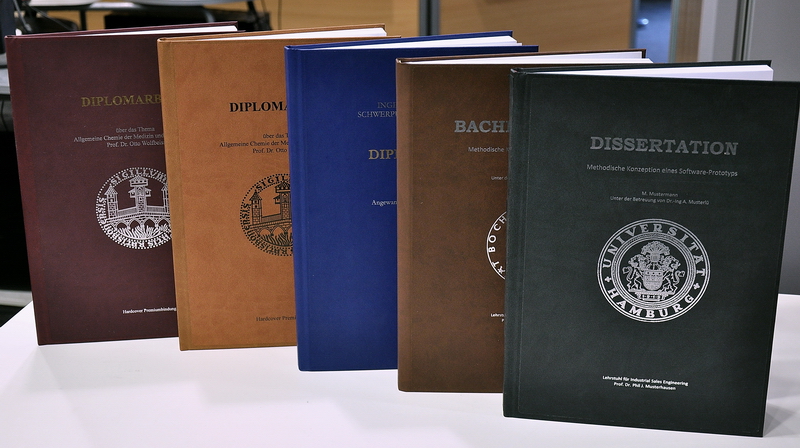
Suche Schriftart für Prägung Bachelorarbeit (Bild anbei)
da ich meine Bachelorarbeit am Montag drucken und binden lassen möchte, suche ich eine Schriftart für die Prägung. Am besten gefällt mir dabei die Schriftart, welche hier bei "DISSERTATION" verwendet wurde. Vor allem das "T" ist sehr markant.
Nach der Überschrift "Dissertation" wird eine serifenlose Schrift benutzt oder sehe ich das falsch? Möchte einfach nur, dass die silberne Prägung auf dem schwarzen Veloursleder gut zur Geltung kommt und etwas altertümlich (wenn man das so sagen kann) wirkt.
Das Ganze wird mit einer Folieprägung realisiert, einzige Voraussetzungen sind diese und ich hab am Telefon noch erfahren, dass die Schrift nicht "zu schwungvoll sein soll", was jedoch bei mir nicht der Fall ist:
Ich würde mal auf sowas wie Bookman tippen, zumal, wenn es häufiger vorkommt, dass Word-Dokumente verwendet werden :)
@Norbert: Vielen Dank für die Font - das sollte sie dann wohl sein! :-D
Möglicherweise handelt es sich um die Bookman von URWPP. Viele dieser Arbeiten werden mit LaTeX gesetzt und dabei werden dann die public domain Schriften aus dem Base 35 Paket von URWPP verwendet. Hier mal der Link auf einige freie Schriften von URWPP (aber nicht alle sind public domain): http://www.artifex.com/downloads/